Jedna dobrze wyróżniona linia potrafi sprawić, że post zatrzyma uwagę, ale ozdobne litery łatwo zamienić w nieczytelny chaos. Wyjaśnię, jak działają czcionki na Facebooka, które style mają sens w postach, komentarzach, relacjach i grupach oraz jak korzystać z nich bez problemów z polskimi znakami i dostępnością.
Najważniejsze zasady dobrego formatowania tekstu na Facebooku
- To nie są prawdziwe fonty, lecz specjalne znaki Unicode kopiowane do serwisu.
- Pogrubienie i prosty krój bezszeryfowy zwykle sprawdzają się najlepiej w nagłówkach i wezwaniach do działania.
- Polskie znaki mogą nie występować w każdym stylu, dlatego tekst trzeba sprawdzić przed publikacją.
- Ozdobne litery stosuj oszczędnie, bo utrudniają wyszukiwanie, kopiowanie i odczyt przez czytniki ekranowe.
- Facebook nie pozwala dowolnie zmieniać fontu w każdym rodzaju publikacji, a dostępne opcje zależą od miejsca i urządzenia.
Czy na Facebooku można zmienić krój pisma
W zwykłym poście na profilu lub stronie Facebook zazwyczaj nie daje możliwości wybrania konkretnej rodziny fontów, tak jak w programie graficznym. Tekst jest wyświetlany krojem ustalonym przez platformę, a jego wygląd może nieco różnić się między aplikacją mobilną, przeglądarką i systemem operacyjnym.
Popularne generatory stylowego tekstu działają inaczej. Nie zmieniają fontu po stronie Facebooka, tylko zamieniają zwykłe litery na podobnie wyglądające znaki Unicode. Dzięki temu po skopiowaniu tekst zachowuje wizualny styl w poście lub komentarzu, choć technicznie nadal jest zwykłym tekstem.
To rozwiązanie jest wygodne, ale ma granice. Część znaków pochodzi z zestawów przeznaczonych pierwotnie do zapisu matematycznego, dlatego nie każdy telefon, czytnik ekranowy ani wyszukiwarka interpretuje je tak samo jak standardowe litery.
Jak używać ozdobnych liter krok po kroku
Najprostszy sposóbwymaga generatora tekstu Unicode. Ja traktuję go jako narzędzie do akcentowania krótkich fragmentów, a nie do stylizowania całej wypowiedzi.
- Wpisz lub wklej tekst do generatora.
- Wybierz prosty styl, na przykład pogrubienie, kursywę albo krój bezszeryfowy.
- Skopiuj gotowy wariant.
- Wklej go do posta, komentarza, opisu profilu lub relacji.
- Sprawdź tekst na telefonie i komputerze, zanim go opublikujesz.
Przykładowo zwykły napis NOWA PRACA można zastąpić formą 𝗡𝗢𝗪𝗔 𝗣𝗥𝗔𝗖𝗔 albo delikatniejszą wersją 𝘕𝘰𝘸𝘢 𝘱𝘳𝘢𝘤𝘢. Pierwszy wariant mocniej przyciąga wzrok, drugi wygląda spokojniej i lepiej pasuje do treści artystycznych lub edukacyjnych.
Przy dłuższym tekście lepiej zostawić standardowe litery i wyróżnić tylko pierwsze zdanie, śródtytuł lub najważniejszą informację. Jedna ozdobna linia działa jak akcent typograficzny, natomiast cały post zapisany nietypowym alfabetem często męczy wzrok.
Które style najlepiej pasują do publikacji
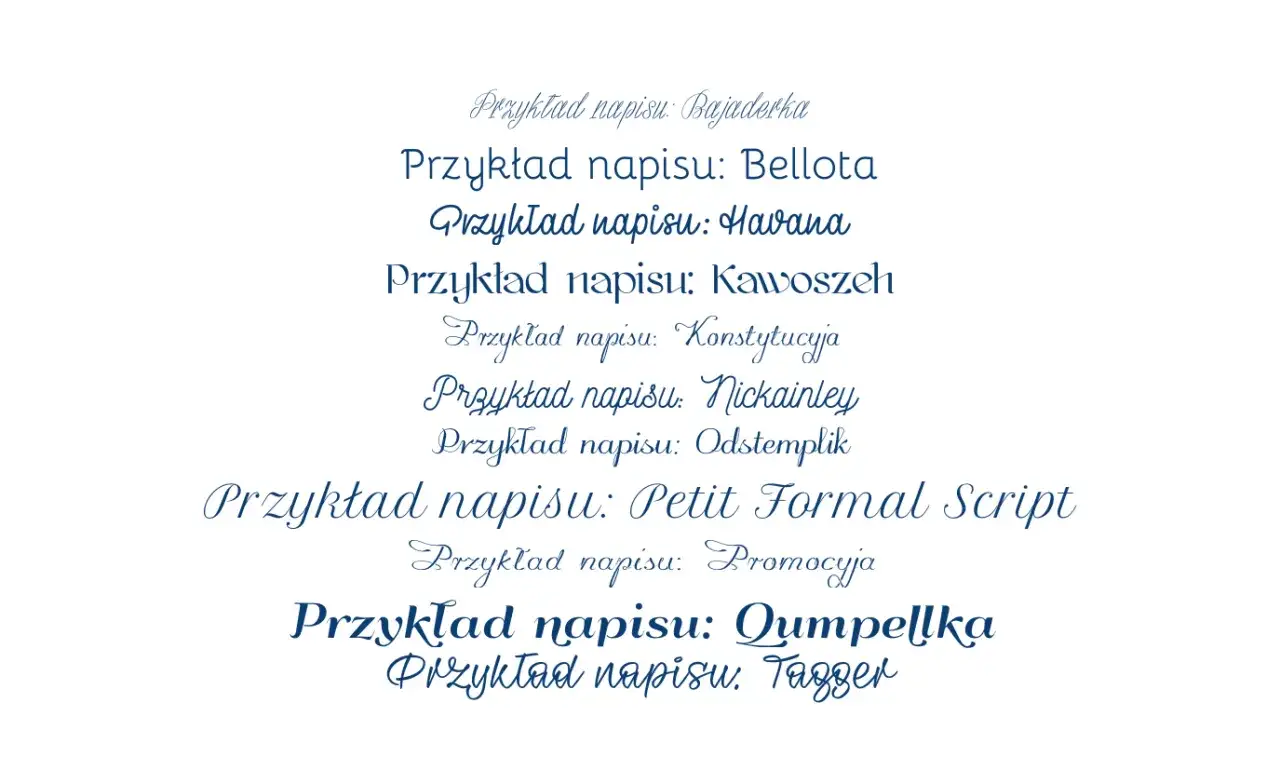
Dobór stylu powinien wynikać z charakteru treści, a nie z liczby efektów dostępnych w generatorze. W liternictwie liczy się przede wszystkim hierarchia, czyli jasne pokazanie, co odbiorca ma przeczytać najpierw.
| Styl | Najlepsze zastosowanie | Moja ocena |
|---|---|---|
| Pogrubiony bezszeryfowy | Nagłówki, daty, ceny, wezwania do działania | Najbardziej uniwersalny i czytelny |
| Kursywa | Cytaty, krótkie dopowiedzenia, nastrojowe wpisy | Subtelna, ale słabsza w małym rozmiarze |
| Szeryfowy | Treści kulturalne, historyczne i eleganckie komunikaty | Efektowny w krótkich fragmentach |
| Pismo odręczne | Zaproszenia, posty lifestyle’owe, rękodzieło | Ma klimat, lecz szybko traci czytelność |
| Gotycki lub blackletter | Muzyka, tatuaż, moda alternatywna, wydarzenia tematyczne | Wyrazisty, ale bardzo niszowy |
| Obramowania i symbole | Krótkie nagłówki, konkursy, komunikaty promocyjne | Łatwo z nimi przesadzić |
W przypadku strony o sztukach wizualnych dobrze sprawdzi się połączenie standardowego tekstu z jednym eleganckim nagłówkiem. Na przykład NOWA WYSTAWA można wyróżnić pogrubieniem, a opis pozostawić zwykłym krojem. Taki kontrast przypomina pracę z plakatem: jeden mocny element prowadzi wzrok, a reszta daje mu oddech.
Unikałbym natomiast całych akapitów w stylu gotyckim, obwiedzionym symbolami lub zapisanym bardzo dekoracyjnym pismem. To rozwiązania dobre na krótką nazwę wydarzenia, nie na instrukcję, opis obrazu czy dłuższą historię.
Polskie znaki są najczęstszą pułapką
Wiele stylów Unicode obsługuje przede wszystkim podstawowe litery alfabetu łacińskiego. Po wpisaniu słowa „malarstwo” efekt może wyglądać dobrze, ale przy wyrazach „źródło”, „piękno” albo „łąka” część znaków może pozostać zwykła lub wyświetlić się jako pusty kwadrat.
To nie musi oznaczać błędu generatora. Nie każdy ozdobny zestaw ma komplet znaków ą, ć, ę, ł, ń, ó, ś, ź i ż. Właśnie dlatego zawsze sprawdzam cały gotowy napis, a nie tylko pierwszy podgląd.
Jak szybko sprawdzić poprawność
- Wpisz próbne zdanie zawierające wszystkie polskie znaki.
- Skopiuj je do Facebooka i obejrzyj w aplikacji mobilnej.
- Sprawdź, czy litery mają podobną wysokość i grubość.
- Zobacz, czy znaki nie zamieniły się w kwadraty, pytajniki lub zwykłe litery.
- Przeczytaj tekst po publikacji z włączonym powiększeniem ekranu.
Jeżeli choć jeden ważny wyraz wygląda źle, wybierz prostszy wariant. Czytelność zawsze wygrywa z dekoracją, zwłaszcza gdy post ma przekazać termin, nazwę dzieła, nazwisko artysty albo datę wydarzenia.
Gdzie takie formatowanie działa najlepiej
Ozdobne znaki mogą być użyteczne w postach, komentarzach, krótkim opisie profilu i nazwach wydarzeń, ale ich działanie zależy od rodzaju publikacji. W relacjach Facebook oferuje własne narzędzia tekstowe, więc tam lepiej korzystać z dostępnych krojów, kolorów i układów zamiast wklejać przypadkowe znaki.
W grupach mogą pojawiać się dodatkowe opcje formatowania tekstu, takie jak pogrubienie, kursywa, nagłówki lub cytaty. Ich dostępność bywa zależna od wersji interfejsu i typu grupy, dlatego przed publikacją warto sprawdzić, czy wybrany styl zachował się w podglądzie.
| Miejsce publikacji | Najlepsze rozwiązanie | Na co uważać |
|---|---|---|
| Post na profilu | Krótki pogrubiony nagłówek Unicode | Nie stylizować całego tekstu |
| Strona marki lub pracowni | Stały, oszczędny schemat wyróżnień | Nadmierna dekoracyjność osłabia profesjonalny odbiór |
| Grupa | Natywne formatowanie, jeśli jest dostępne | Opcje mogą różnić się między urządzeniami |
| Komentarz | Jedno krótkie wyróżnienie | Ozdobne alfabety mogą utrudniać wyszukiwanie |
| Relacja | Narzędzia tekstowe Facebooka | Wklejony Unicode może wyglądać nierówno |
W praktyce najwięcej sensu widzę w postach edukacyjnych i promocyjnych. Pogrubiona data warsztatów, nazwa techniki albo hasło „zapisy do piątku” tworzą punkty orientacyjne, dzięki którym odbiorca szybciej rozumie komunikat.
Czego nie widać na pierwszy rzut oka
Stylowy tekst jest technicznie innym ciągiem znaków niż zwykły napis. Może więc gorzej działać przy kopiowaniu, wyszukiwaniu treści, automatycznym tłumaczeniu i odczycie przez czytnik ekranowy. Według zaleceń Unicode takie warianty liter są związane głównie z zapisem matematycznym, a do zwykłego tekstu lepiej używać standardowych liter i prawdziwego formatowania.
Nie oznacza to, że trzeba całkowicie rezygnować z efektów. Trzeba tylko rozdzielić funkcje. Ozdobne znaki służą do przyciągnięcia uwagi, natomiast zasadnicza treść powinna pozostać łatwa do odczytania, skopiowania i zrozumienia.
Odradzam też generowanie całych zdań wielkimi ozdobnymi literami. Taki zapis nie tylko obciąża wzrok, lecz także może wyglądać jak krzyk. Jeszcze mniej praktyczne są znaki łączące, które tworzą pozorne podkreślenia lub przekreślenia, bo na niektórych urządzeniach przesuwają się nad literami.
Jeżeli publikujesz ważne informacje, sprawdź również link, numer telefonu i nazwę wydarzenia w zwykłym tekście. Najważniejszych danych nie chowaj wyłącznie w dekoracyjnym alfabecie, ponieważ część odbiorców może ich nie odczytać albo nie będzie w stanie ich skopiować.
Jak stworzyć spójny styl bez przesady
Najlepszy efekt daje prosty system, na przykład jeden styl dla nagłówków, standardowy tekst dla opisu i pojedynczy symbol do zaznaczania listy. Dzięki temu odbiorca po kilku publikacjach rozpoznaje sposób komunikacji, a profil wygląda bardziej świadomie.
- Wybierz maksymalnie jeden lub dwa style dla całej strony.
- Wyróżniaj tylko najważniejszy fragment, najlepiej do 3-7 słów.
- Nie zapisuj całego posta ozdobnymi literami.
- Testuj polskie znaki przed publikacją.
- Zachowaj zwykły tekst przy danych, instrukcjach i nazwach własnych.
Moja ulubiona zasada jest prosta: jeżeli po usunięciu efektu post traci sens, problem leży w treści, nie w foncie. Dobre liternictwo porządkuje komunikat i buduje nastrój, ale nie powinno zmuszać odbiorcy do rozszyfrowywania liter.
Najbezpieczniejszy wybór to czytelny styl bezszeryfowy lub delikatna kursywa użyta w jednym miejscu. Takie rozwiązanie pozwala połączyć charakter wizualny z funkcjonalnością, a właśnie ten kompromis sprawdza się na Facebooku najlepiej.